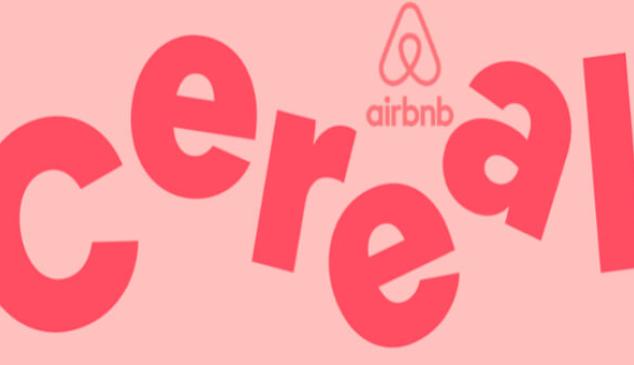
Airbnb presenta Airbnb Cereal. Y, aunque el nombre pueda llevar a engaño, no se trata de un nuevo servicio de desayuno. Nada Más lejos. Hablamos de diseño y de una nueva marca que apuesta por crear una tipografía propia.
Airbnb Cereal
Airbnb se ha marcado un objetivo: ser más legible y accesible para cada vez más gente. Tanto en soportes digitales como en Publicidad Exterior. Bajo estas premisas han creado la tipografía Cereal, de la familia sans-serif y disponible en hasta seis pesos diferentes (fina, negrita, extra negrita...).
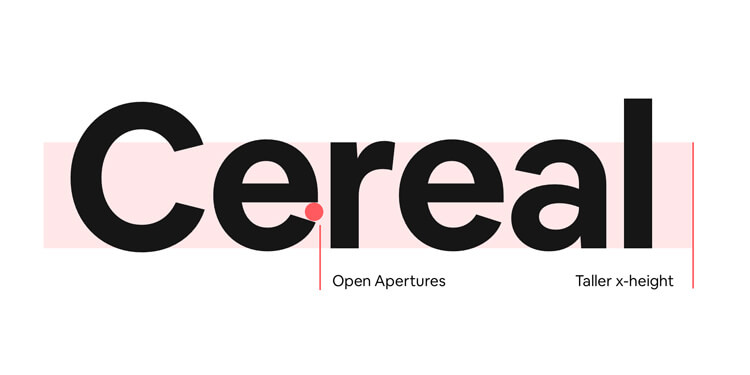
La nueva tipografía de Airbnb tiene un eje vertical más alto que la anterior que usaba la marca y una anchura entre letras mayor. Los gaps entre caracteres son más pequeños. A partir del mes que viene la veremos en todos los soportes digitales de la compañía (webs y aplicaciones para dispositivos móviles)...
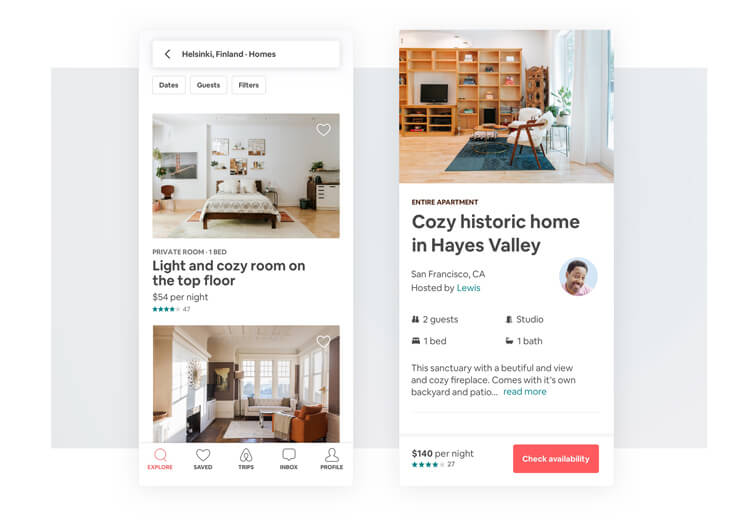
Y también en print:
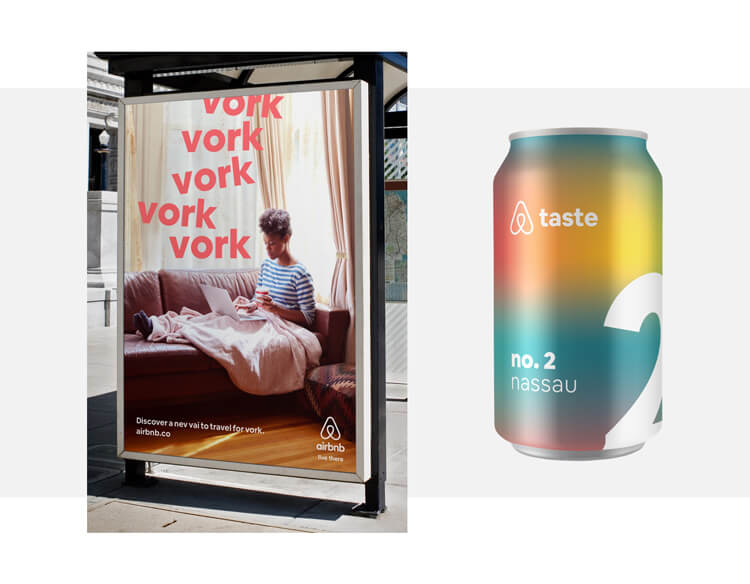
Asegura la marca que se trata de ser accesible para más gente en consonancia con el claim “Airbnb for everyone”.
¿Por qué Cereal?
El nombre de la nueva tipografía no ha sido aleatorio. Se remonta a la campaña creada por los Co-Fundadores de Airbnb en 2008.
Consistió en el diseño y la venta de cereales coleccionables de Barack Obama y John McCain durante la precampaña de las presidenciales de Estados Unidos. Desde Airbnb, aseguran que fue una campaña que evitó el cierre de la compañía. “Cereal ha salvado a la compañía y ha inspirado el core de la marca que consiste en pensar cómo resolver problemas de maneras inesperadas. La elección del nombre para la nueva tipografía ha sido algo natural”, han asegurado.
Airbnb no es la única
La apuesta por Airbnb Cereal sigue una tendencia de cada vez más marcas, tanto tradicionales como start ups que nacen en el mundo digital que apuestan por crear su propia tipografía. Uno de esos ejemplos es YouTube que presentó su primera tipografía propia YouTube Sans el año pasado.
Coca-Cola también lo hizo en enero de este año.